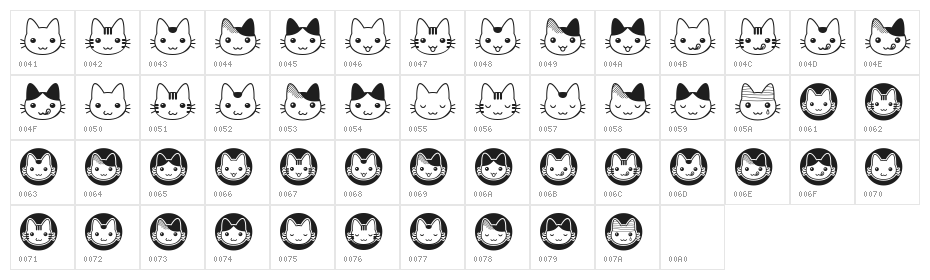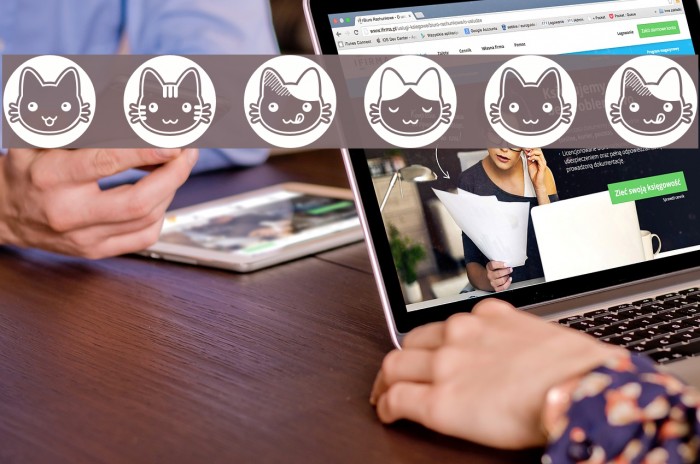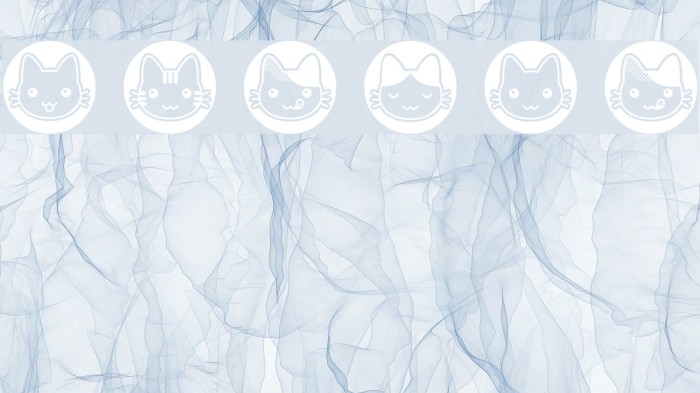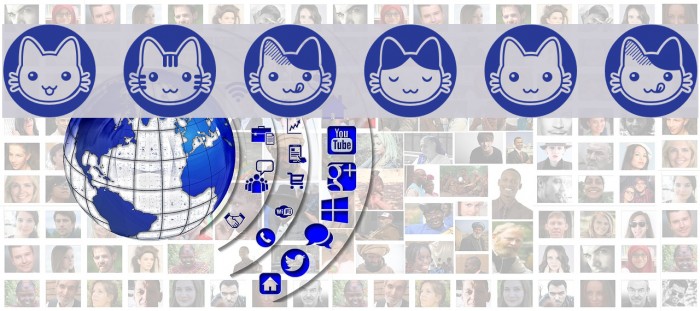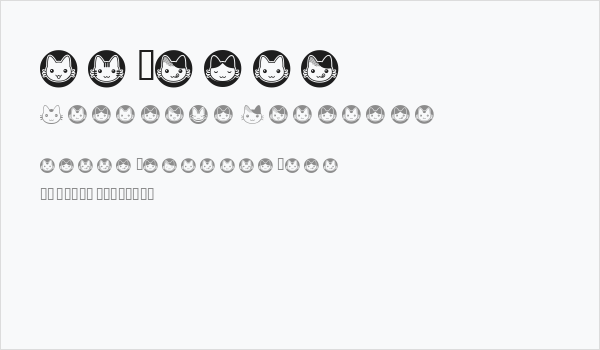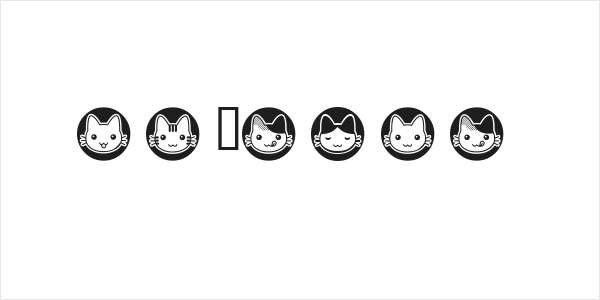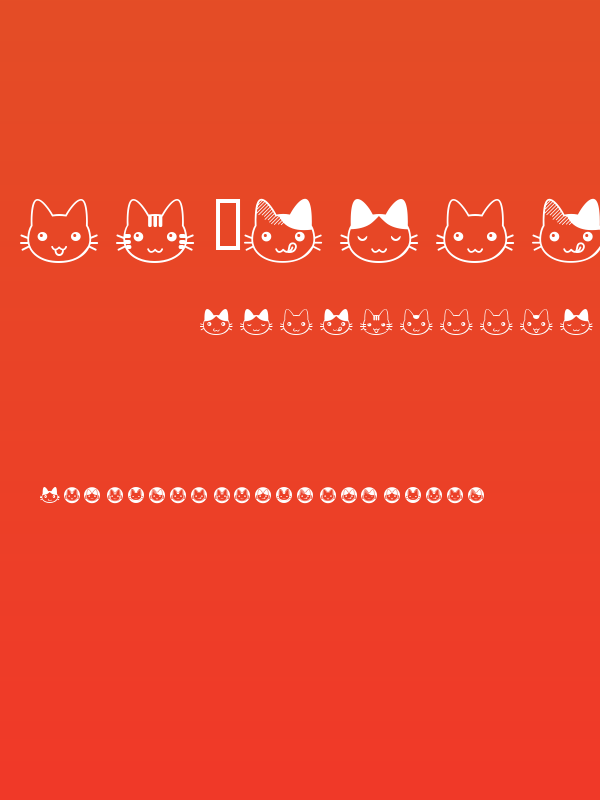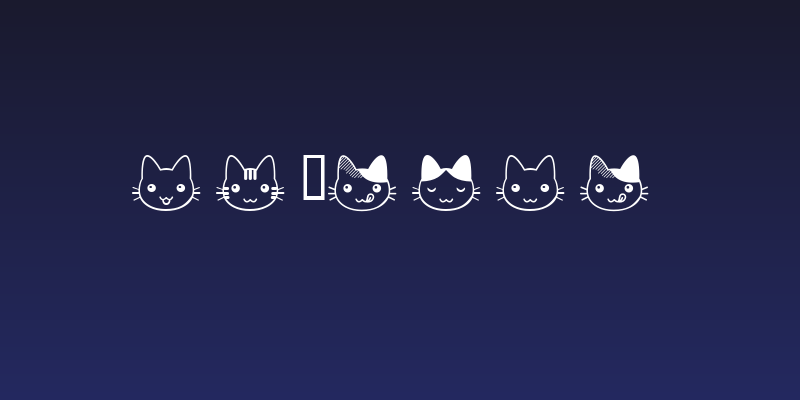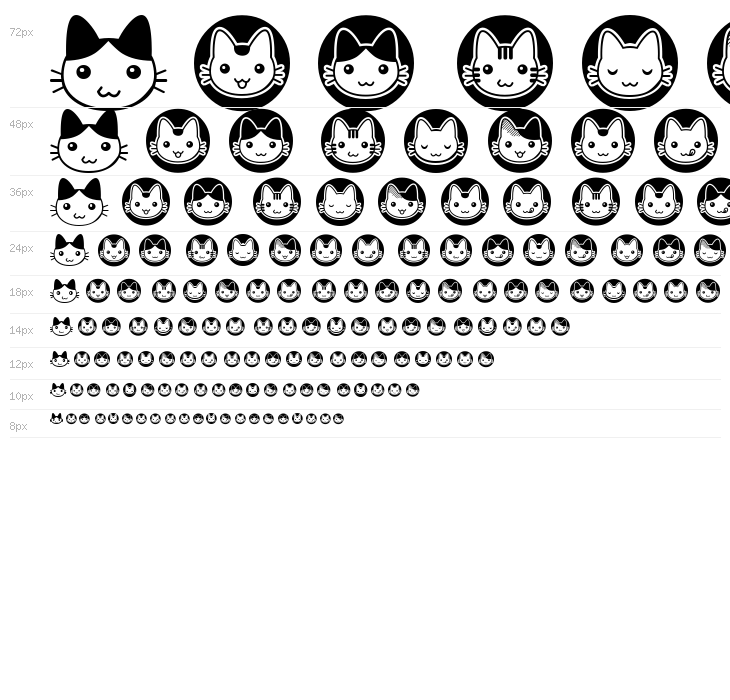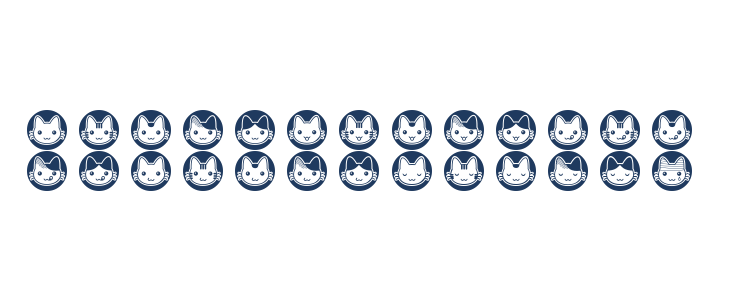
fb_nyan Font
| Stile generale | Playful, Cute, Decorative |
| Caso d'uso | Logos, Headlines, Decorative elements |
| Progetti proposti | Children’s books, greeting cards, playful branding, stickers, social media graphics, and decorative headings. |